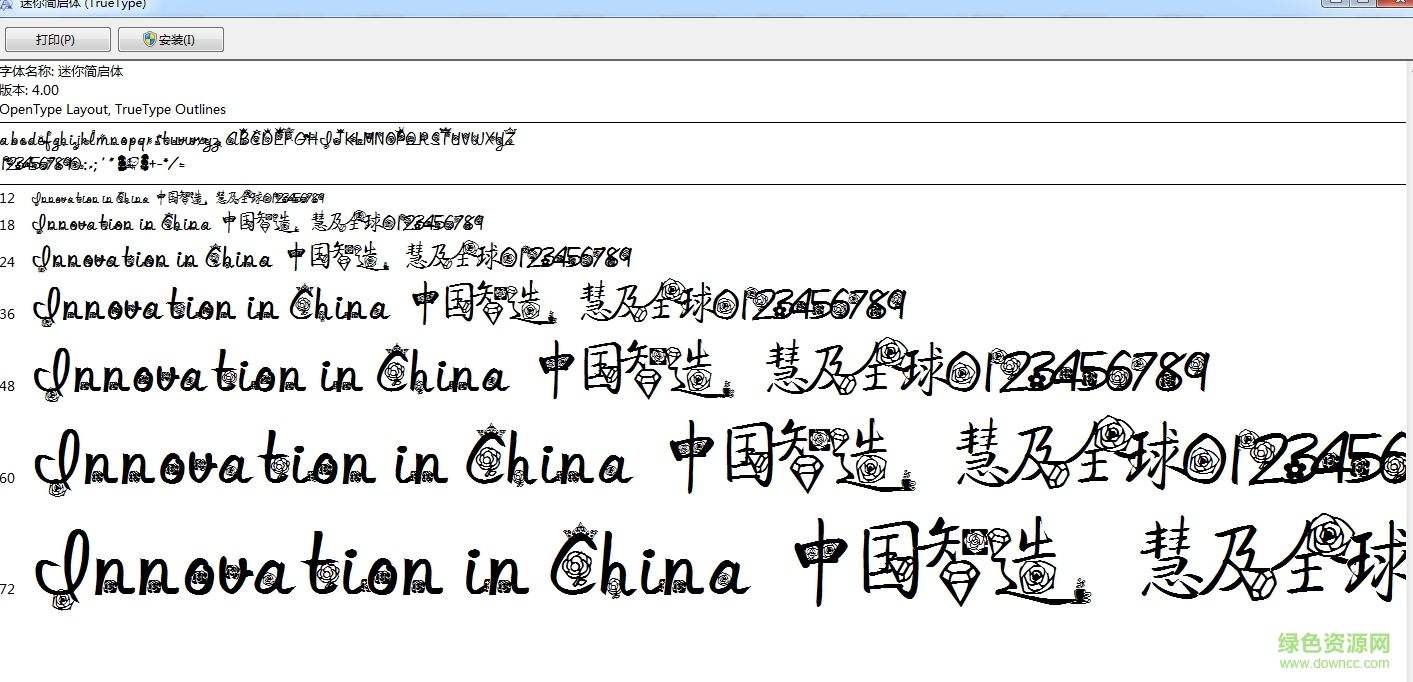
玫瑰鉆戒愛情體字體
玫瑰鉆戒愛情字體是一款粗細(xì)勻稱的個(gè)性字體,清新優(yōu)雅,實(shí)用性與美觀性兼?zhèn)洌盟茞矍樘鹛鹈勖?,廣泛應(yīng)用于廣告設(shè)計(jì)、宣傳海報(bào)、ppt、影視制作等領(lǐng)域!有需要者趕緊來綠色資源網(wǎng)下載吧!
玫瑰鉆戒愛情字體字型飽滿,間隔均衡,加鋒較小,整體美觀而不落俗套!